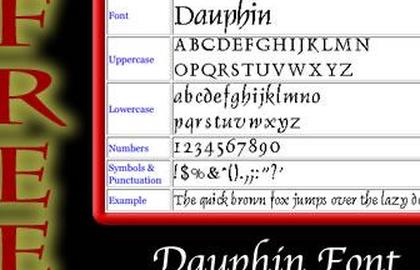
Бесплатный шрифт Дофин
Если вы ищете красивую декоративную надпись для своей копии, бесплатный шрифт dauphin может быть именно тем, что вам нужно. Несмотря на пеструю историю, шрифт оказался полезным и популярным в Интернете и в печати.
Несовершенная копия
В отличие от многих других шрифтов, которые предположительно бесплатны , вам будет сложно найти место, где можно купить Dauphin. Шрифт на самом деле представляет собой искаженную версию шрифта Linotype «Delphin», основанного на каллиграфии, для которого характерны длинные изогнутые штрихи букв, таких как «h» и «n», а также более широкий набор заглавных букв в римском стиле. Технически это шрифт с засечками, хотя многие буквы выглядят без засечек (особенно строчные).
Во время сражений 1990-х годов за стандартизацию типов шрифтов (включая TrueType, OpenType, Microsoft, Apple и Adobe) была одна компания под названием Corel, которая пыталась конкурировать с другими издательскими компаниями. С такими приложениями, как CorelDraw и CorelWrite, они не хотели получать лицензии от других компаний на использование Delphin — поэтому они просто создали свою собственную версию, известную как Dauphin. Есть небольшие различия — в основном в том, как заканчиваются штрихи, — но для непрофессионала эти два шрифта почти полностью идентичны.
В то время как Corel не пережил трудности краха доткомов, шрифт Dauphin выжил, и теперь он доступен бесплатно на многих веб-сайтах. В то время как на многих «бесплатных» веб-сайтах со шрифтами есть либо любительские шрифты, либо контрабандные версии (что делает их загрузку равносильной краже), Dauphin — один из немногих, который создан профессионально и к тому же доступен бесплатно — на самом деле, обширный поиск в Google показывает нет места, где вы могли бы купить шрифт.
Где использовать бесплатный шрифт Dauphin
Имейте в виду, что шрифт Dauphin является декоративным. Это означает, что большой блок текста шрифтом будет довольно сложно читать. Он чаще используется в заголовках или для придания плакату духа европейской истории. Плавные штрихи строчных букв в сочетании с сильным, квадратным авторитетом заглавных букв делают его утонченным шрифтом для элегантных сообщений — вероятно, не то, что нужно для приглашения на день рождения ребенка.
Он также немного вычурный и поэтому, вероятно, не подходит для деловых презентаций или более серьезных вывесок. Один из способов, которым вы могли бы попробовать и решить, будет ли шрифт подходящим, — это спросить себя: « Подходят ли цветы к этому знаку/презентации/приглашению/чему-то еще? » шрифт. Если вы действительно решили использовать его для большого количества текста, убедитесь , что вы регулируете высоту строки, пробелы между словами, и кернинг так, чтобы буквы имеют достаточно места , чтобы быть удобочитаемым.
Комбинации
Один из способов, которым шрифт Dauphin действительно может вам помочь, — это использовать его в сочетании с другими шрифтами. Имейте в виду, однако, что использование более двух шрифтов в любом документе является опасным делом с точки зрения дизайна — хотя это допустимо, вам действительно нужно знать, что вы делаете, чтобы это работало. Некоторые дизайнеры выступают за использование шрифтов с засечками и шрифтов без засечек, если вы собираетесь комбинировать шрифты, но опять же будьте осторожны — использование шрифта Dauphin, который является более квадратным, с вертикальным прямоугольным шрифтом, таким как Helvetica , вероятно, будет конфликтовать.